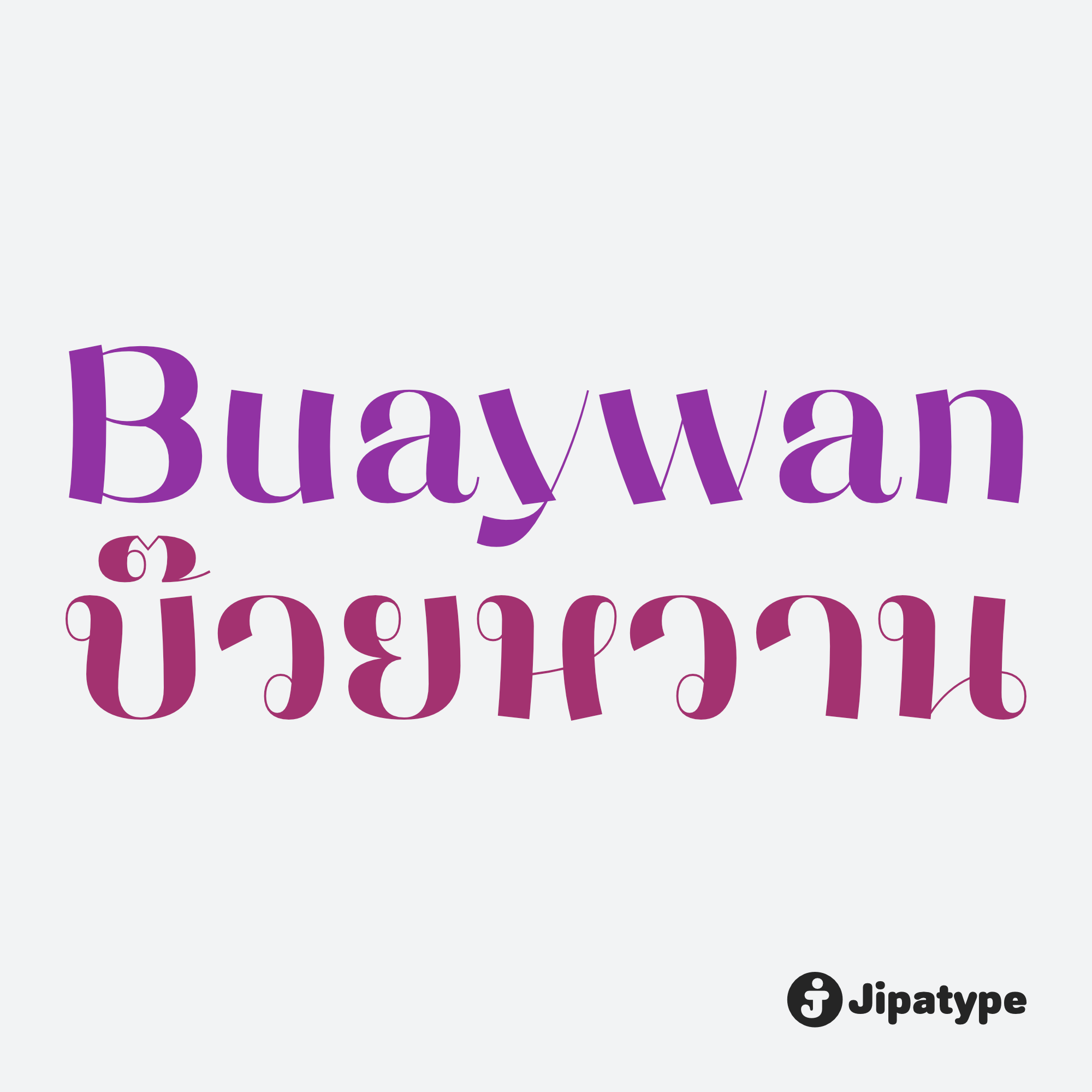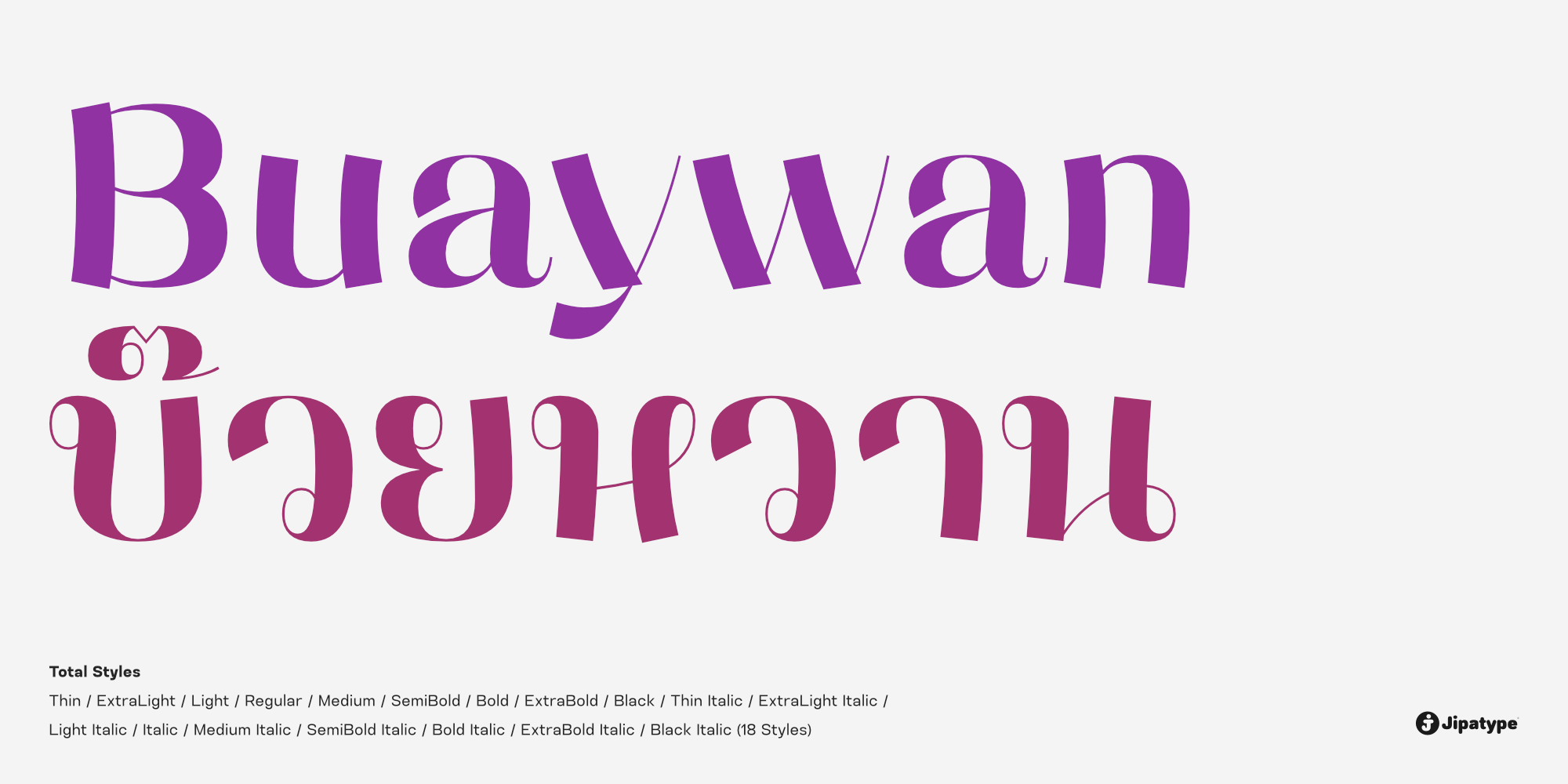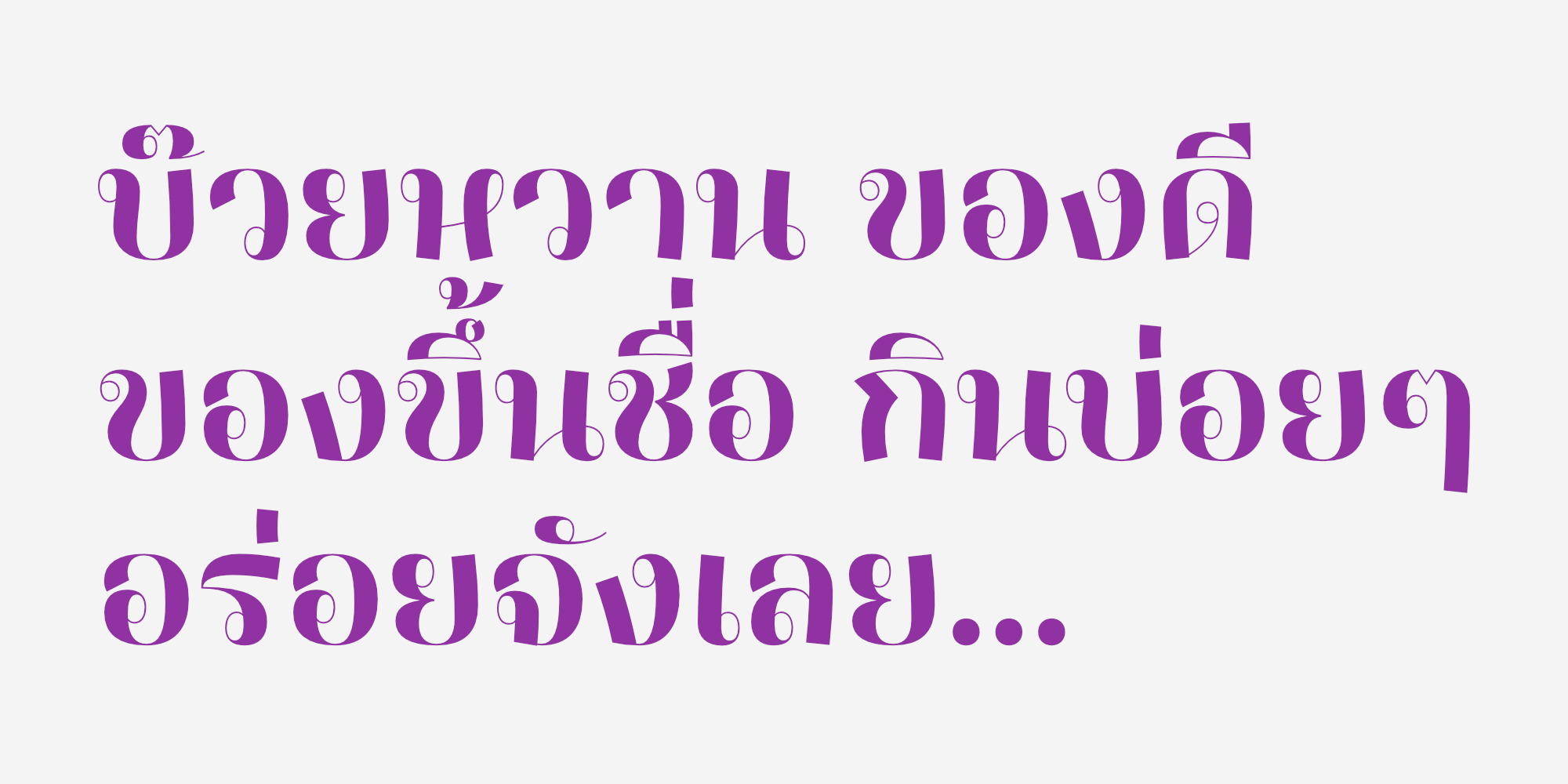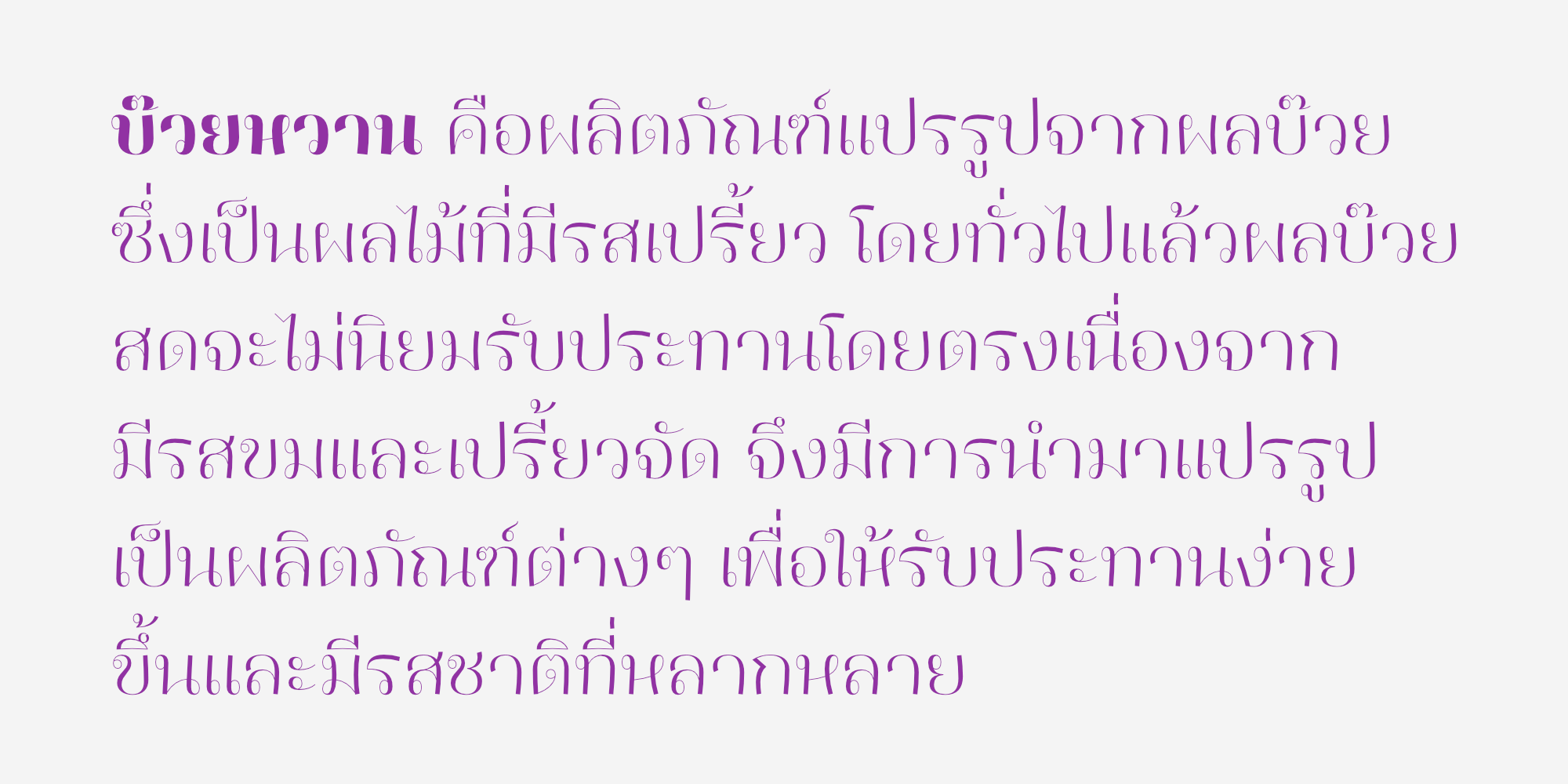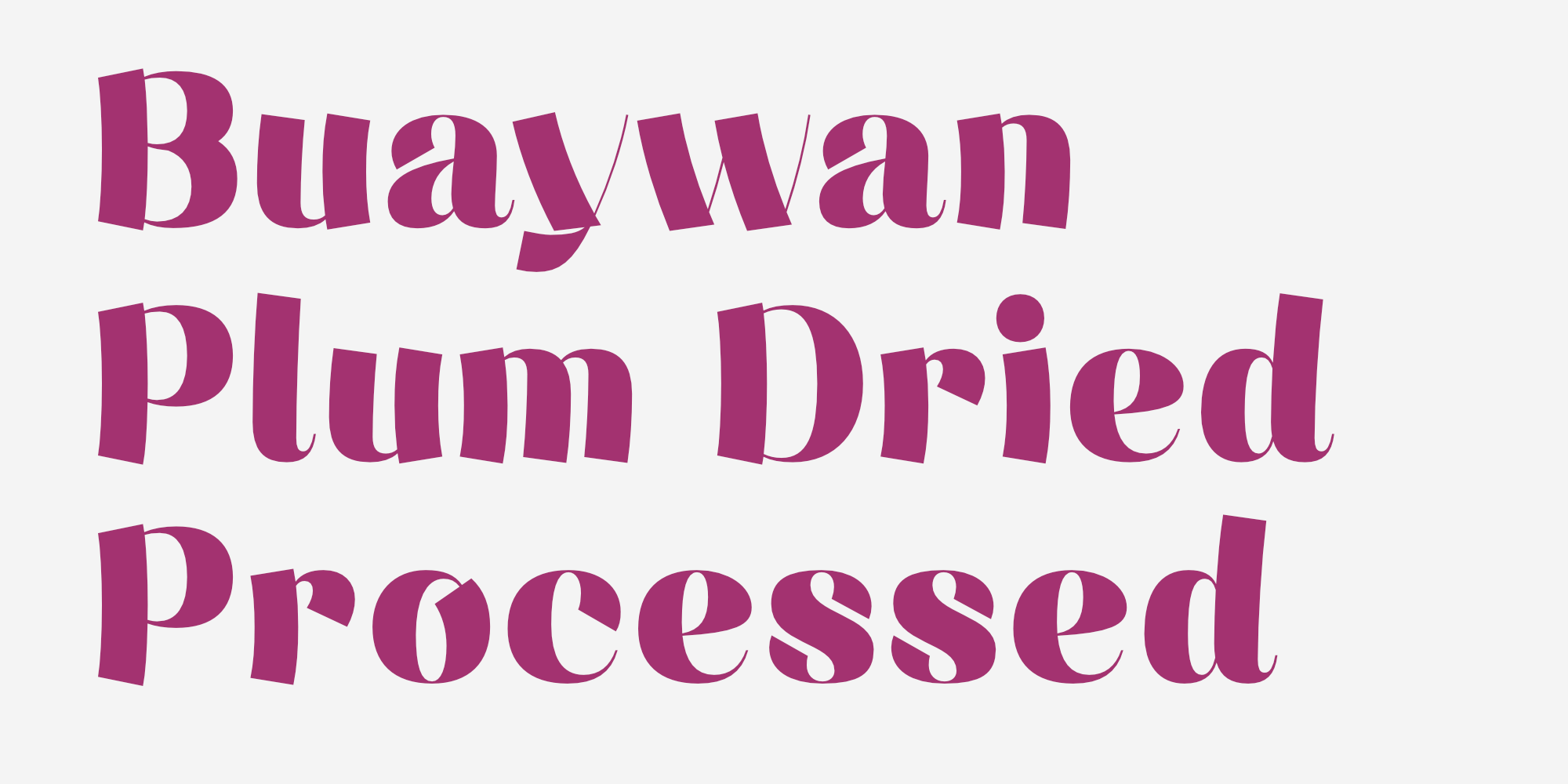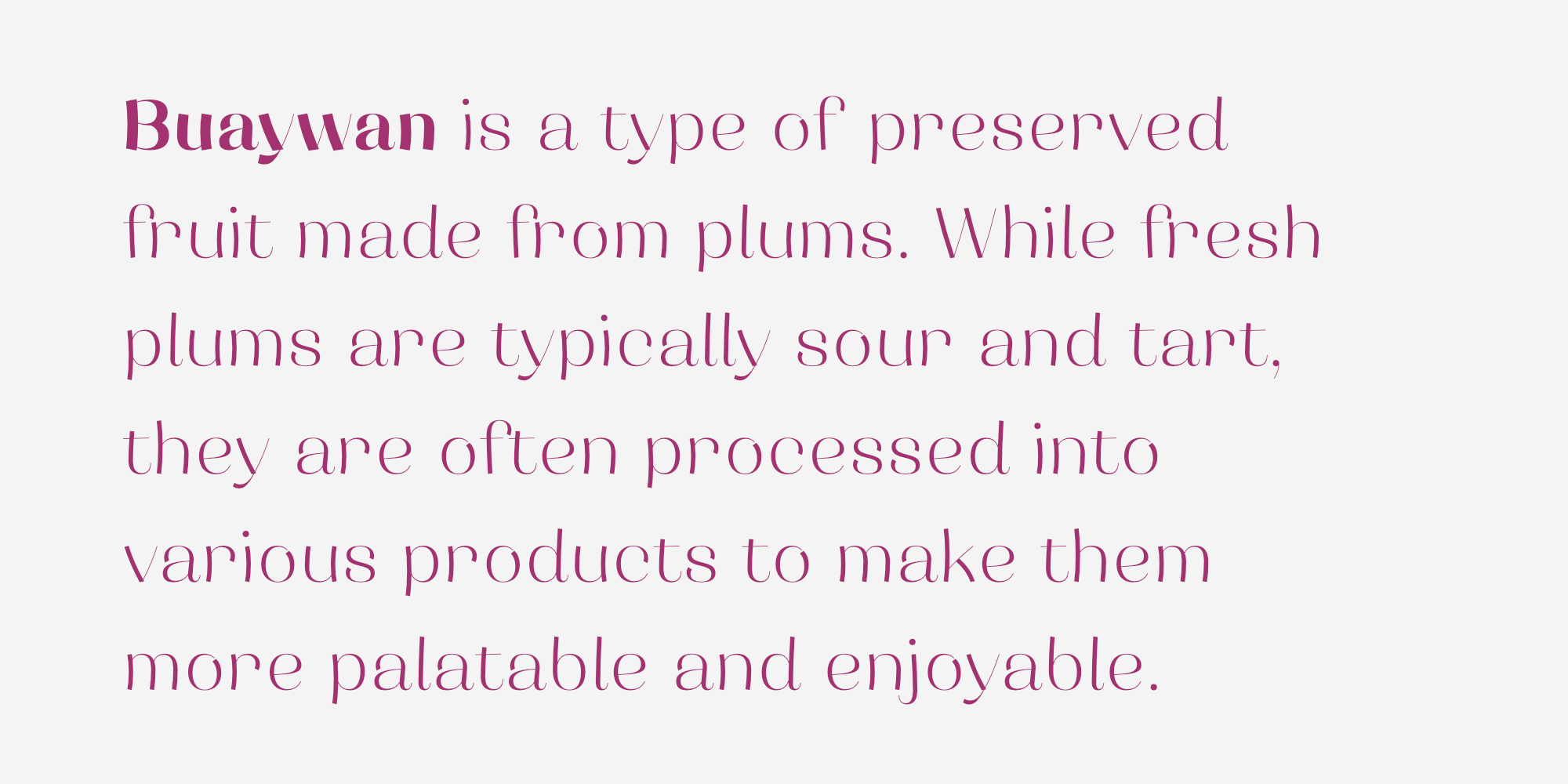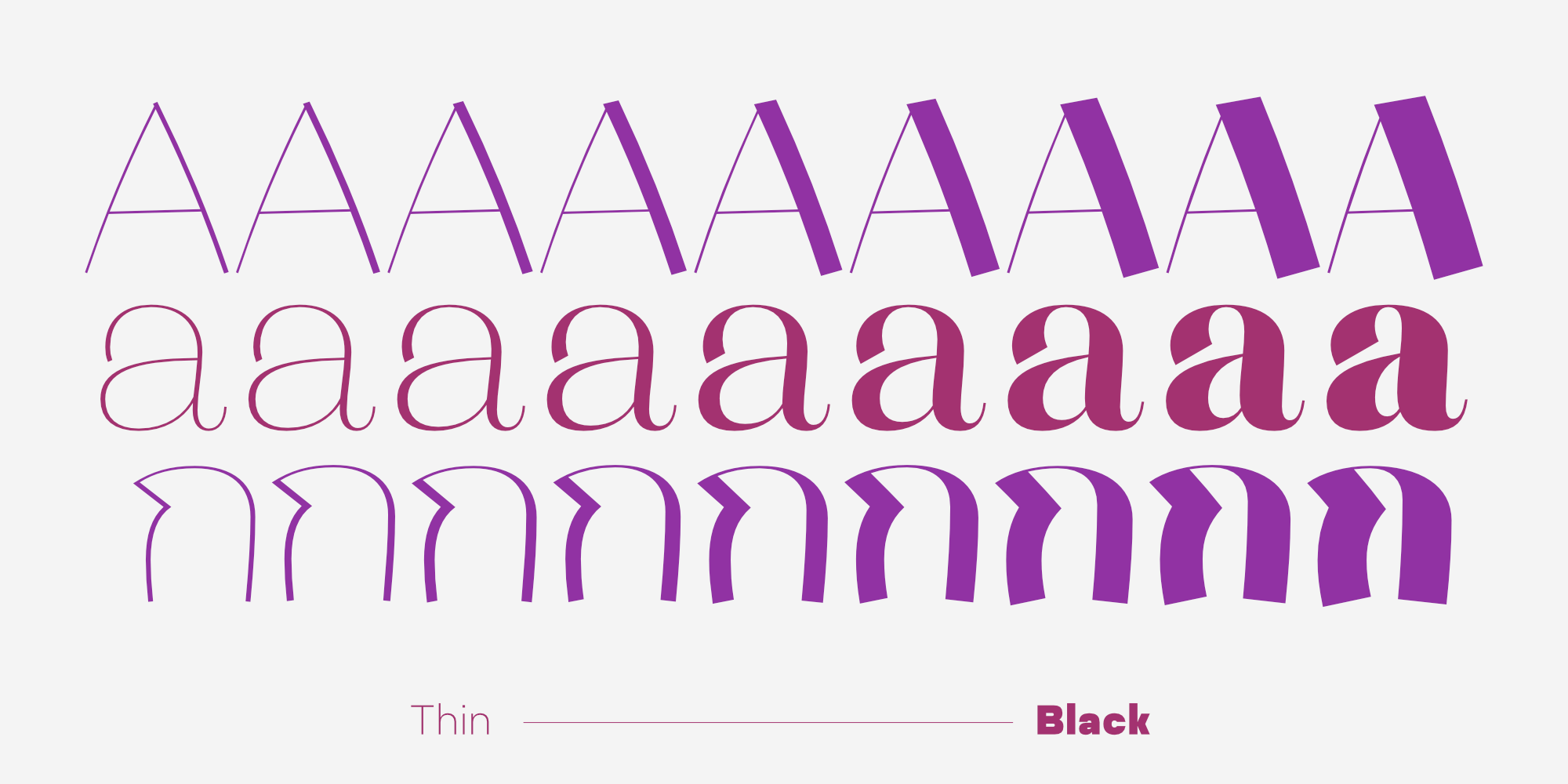
Buaywan เป็นชุดตัวอักษรที่โดดเด่นด้วยลายเส้นที่มีน้ำหนักตัดกันอย่างชัดเจน ให้ความรู้สึกเหมือนการตวัดปลายพู่กันหรือปากกาหัวตัด เส้นสายมีความโค้งมน พลิ้วไหว และดูเป็นธรรมชาติ ซึ่งช่วยลดทอนความแข็งกระด้าง ทำให้ตัวอักษรดูมีความ “หวาน” นุ่มนวล และเป็นมิตร ตามชื่อของฟอนต์
แต่ในขณะเดียวกันก็ยังคงความโฉบเฉี่ยวและทันสมัยในแบบฉบับของ Display Font
ในส่วนของตัวอักษรภาษาไทย ได้รับการออกแบบเป็นสไตล์ “มีหัว” ให้มีความเรียบหรู ทันสมัย และอ่านง่าย มาพร้อมกับน้ำหนักที่หลากหลายตั้งแต่เส้นบางเฉียบที่ให้ความรู้สึกหรูหรา ไปจนถึงน้ำหนักหนาเข้มที่ดูสนุกสนานและสะดุดตา ทำให้สามารถเลือกใช้สร้างอารมณ์ของงานออกแบบได้หลากหลายมิติ
ด้วยบุคลิกที่ดูเก๋ไก๋และมีเสน่ห์ Buaywan จึงเหมาะอย่างยิ่งสำหรับการใช้งานเป็นพาดหัว หรือข้อความที่ต้องการดึงดูดความสนใจ เป็นตัวเลือกที่ยอดเยี่ยมสำหรับงานออกแบบอัตลักษณ์แบรนด์, การออกแบบบรรจุภัณฑ์ โดยเฉพาะกลุ่มสินค้าไลฟ์สไตล์ อาหาร ขนมหวาน หรือเครื่องสำอาง รวมถึงการนำไปใช้ในงานสื่อสิ่งพิมพ์แฟชั่น โปสเตอร์ และกราฟิกบนโซเชียลมีเดียที่ต้องการภาพลักษณ์ที่ดูสดใส มีรสนิยม และเข้าถึงง่าย
ออกแบบโดย : อานุภาพ ใจชำนาญ (Anupap Jaichumnan)